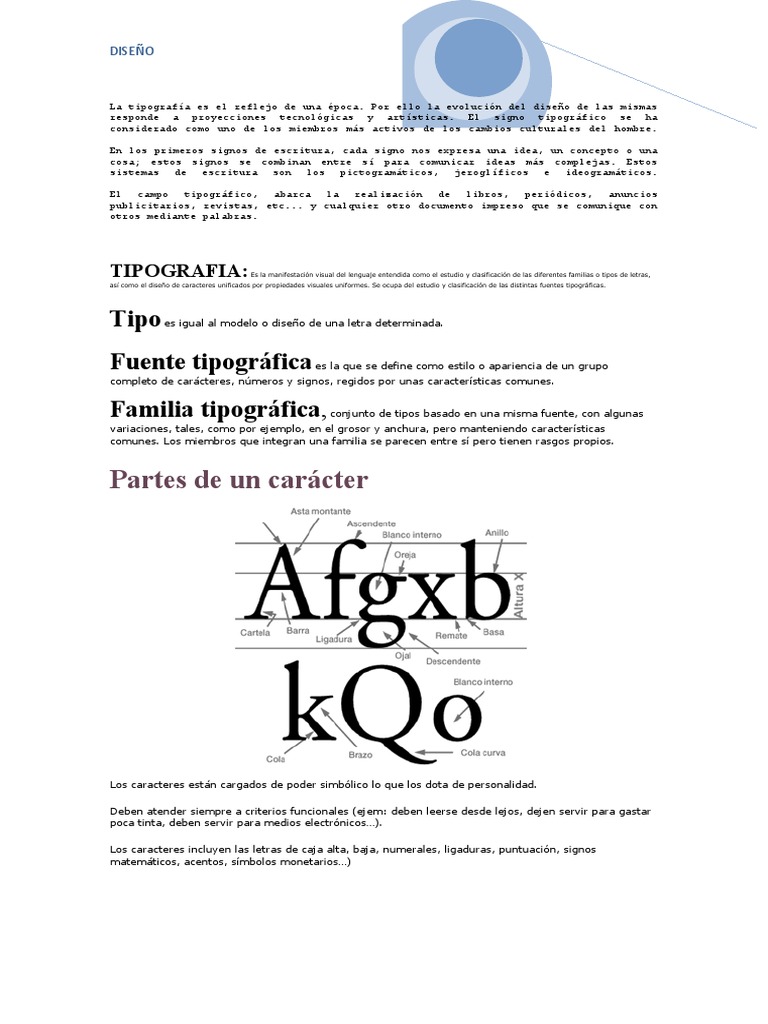
DISEÑO
La tipografía es el reflejo de una época. Por ello la evolución del diseño de las mismas
responde a proyecciones tecnológicas y artísticas. El signo tipográfico se ha
considerado como uno de los miembros más activos de los cambios culturales del hombre.
En los primeros signos de escritura, cada signo nos expresa una idea, un concepto o una
cosa; estos signos se combinan entre sí para comunicar ideas más complejas. Estos
sistemas de escritura son los pictogramáticos, jeroglíficos e ideogramáticos.
El campo tipográfico, abarca la realización de libros, periódicos, anuncios
publicitarios, revistas, etc... y cualquier otro documento impreso que se comunique con
otros mediante palabras.
TIPOGRAFIA: Es la manifestación visual del lenguaje entendida como el estudio y clasificación de las diferentes familias o tipos de letras,
así como el diseño de caracteres unificados por propiedades visuales uniformes. Se ocupa del estudio y clasificación de las distintas fuentes tipográficas.
Tipo   es igual al modelo o diseño de una letra determinada.
Fuente tipográfica  es la que se define como estilo o apariencia de un grupo
completo de carácteres, números y signos, regidos por unas características comunes.
Familia tipográfica, conjunto de tipos basado en una misma fuente, con algunas
variaciones, tales, como por ejemplo, en el grosor y anchura, pero manteniendo características
comunes. Los miembros que integran una familia se parecen entre sí pero tienen rasgos propios.
Partes de un carácter
Los caracteres están cargados de poder simbólico lo que los dota de personalidad.
Deben atender siempre a criterios funcionales (ejem: deben leerse desde lejos, dejen servir para gastar
poca tinta, deben servir para medios electrónicos…).
Los caracteres incluyen las letras de caja alta, baja, numerales, ligaduras, puntuación, signos
matemáticos, acentos, símbolos monetarios…)
DISEÑO
Partes que componen un tipo
Altura de las mayúsculas: Es la altura de las letras de caja alta.
Altura X: Altura de las letras de caja baja, las letras minúsculas, excluyendo los ascendentes y los
descendentes.
Anillo: Es el asta curva cerrada que forman las letras "b, p y o".
Ascendente: Asta que contiene la letra de caja baja y que sobresale por encima de la altura x, tales
como las letras "b, d y k".
Asta: Rasgo principal de la letra que la define como su forma o parte mas esencial.
Astas montantes: Son las astas principales o oblicuas de una letra, tales como la "L, B, V o A".
Asta ondulada o espina: Es el rasgo princial de la letra "S" en mayúscula o "s" en minúscula.
Asta transversal: Rasgo horizontal de las letras "A, H, f o t".
Brazo: Parte terminal que se proyecta horizontalmente o hacia arriba y que no se encuentra incluida
dentro del carácter, tal como se pronuncia en la letra "E, K y L".
Cola: Asta oblicua colgante que forman algunas letras, tales como la " R o K ".
Descendente: Asta de la letra de caja baja que se encuentra por debajo de la línea de base, como
ocurre con la letra "p y g".
Inclinación: Ángulo de inclinación de un tipo.
Línea base: La línea sobre la que se apoya la altura.
Oreja: Es la terminación o terminal que se le añade a algunas letras tales como "g, o y r".
PATA
Trazo diagonal que sirve de apoyo a algunas letras. También se puede llamar cola.
SERIF, REMATE O GRACIA
Trazo terminal de un asta, brazo o cola. Es un resalte ornamental que no es indispensable para la definición del carácter, habiendo alfabetos que carecen de ellos (sans
serif).
UÑA O GANCHO
Final de un trazo que no termina en remate, sino con una pequeña proyección de un trazo.
VÉRTICE
Punto exterior de encuentro entre dos trazos en la parte inferior de la letra.